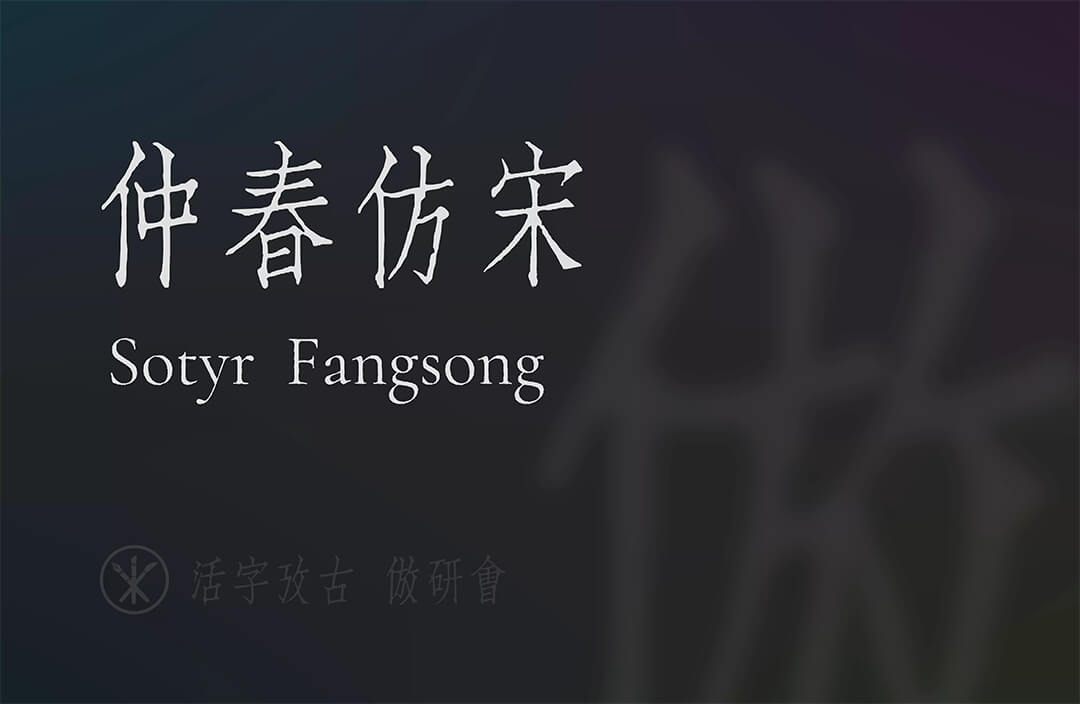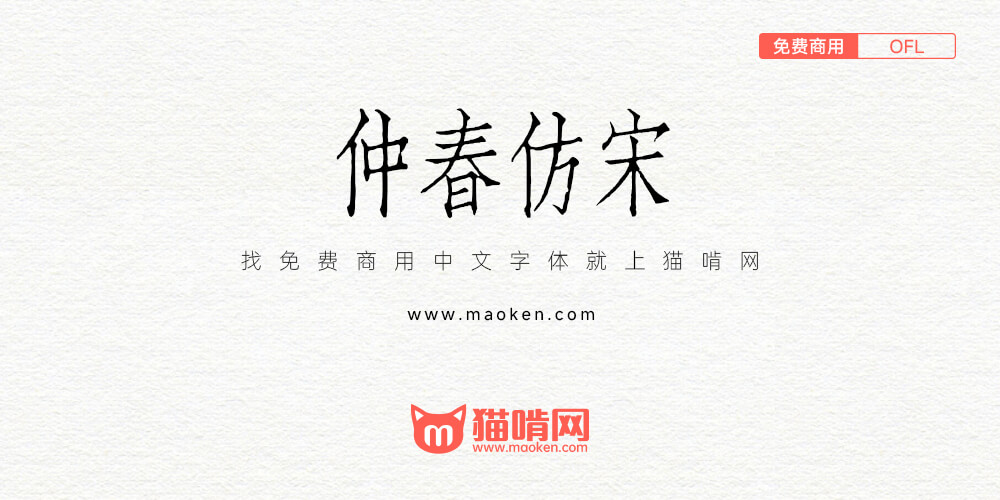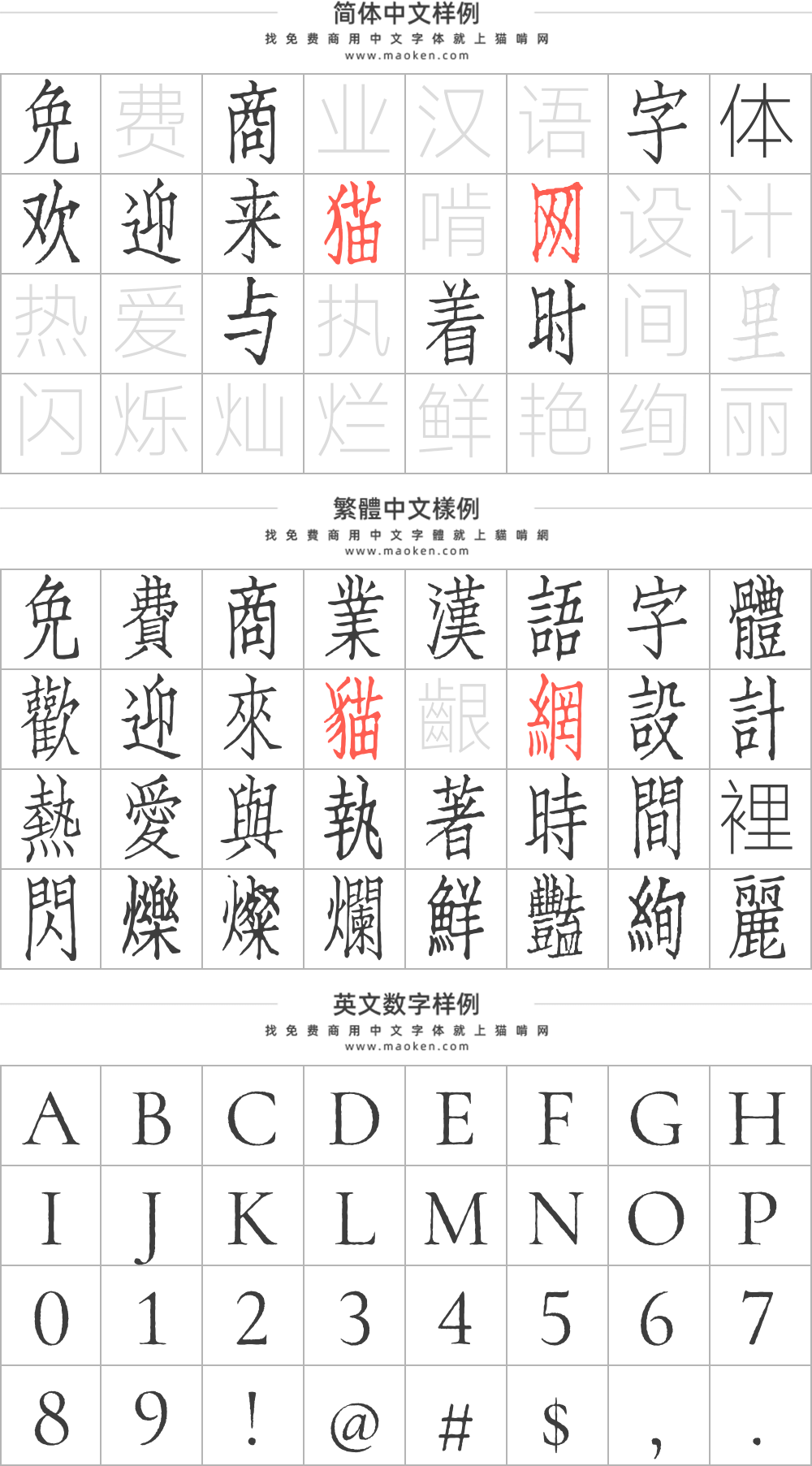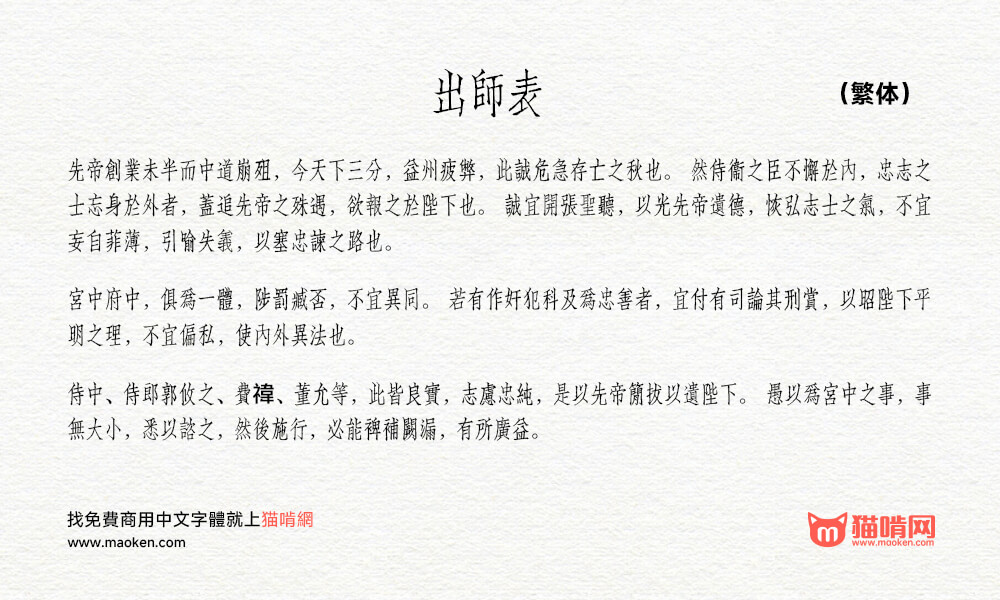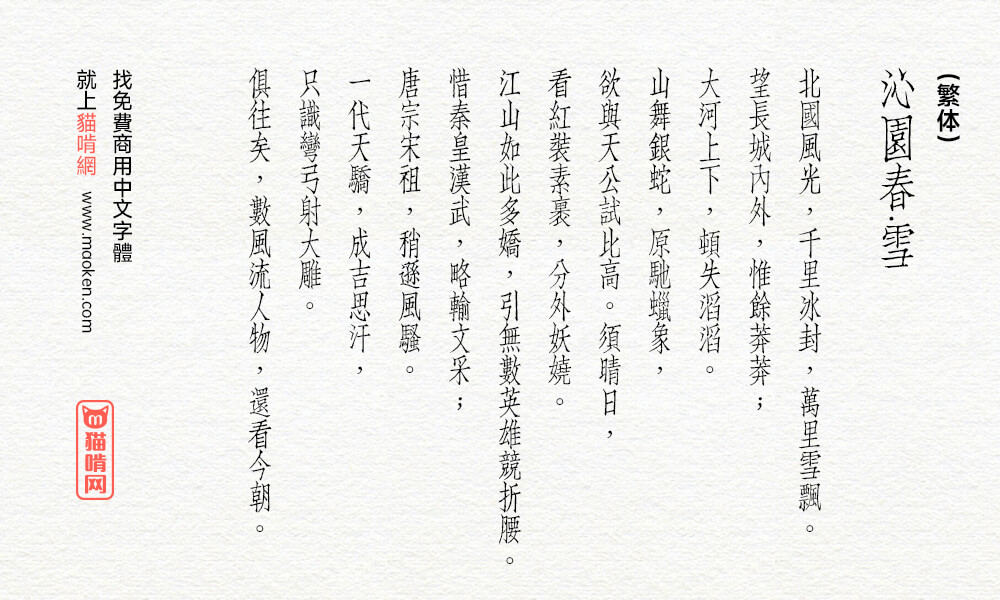
「仲春仿宋」项目是对上世纪聚珍仿宋二号长体铅活字字形进行的数字化。采用直接复刻办法,从印刷品扫描件中提取字形并封装为字体。
项目尚处于开发和测试阶段,其中的缺字、丑字不少,远不及正式版发布的程度。简化字部分是基本没有的,也不太推荐用于现代汉语文本的排版,还请各界朋友多多包涵。
开发故事
若论哪套长体仿宋最为著名?熟谙近现代印刷史的同志,恐怕大都会脱口而出「聚珍仿宋」。不过聚珍仿宋的长体铅字自身又包含多种字号,哪一种最具代表性?这个问题的答案或许在同志们的脑海中能浮现出,但落实到具体字号层面,就不那么好回答了。
聚珍仿宋二号长体铅字,造型妍美多姿,而又因其字号适中,常应用于正文排版而不是标题和夹注。相比于头号字的直健、三号四号字的间架异化处理、五号字的细密,二号字的字形可以说是最丰富地展现了聚珍仿宋家族的风味。同时,上世纪末,聚珍仿宋二号长体经过史云鹏的大力推广,成为了工程类制图常用的手写体。工科出身的朋友们,你们当年有没有练习过呢?
聚珍的头号方体长体、二号方体,市面已有产品,而尚无二号长体产品可用。
在印刷品样本方面,现在开放的电子化扫描件非常多了,缺少的只是对其中的字形进行提取封装的工作。这个工作量不小,所以从今年(2025)1 月开始,我们又合作开发了一种切片工具和一种封装前处理工具,效率大为提升,小组内的同志们拊掌称奇。
总之,「仲春仿宋」是传统汉字美学、印刷和数字化技术、新生产力结合的产物。
问:「为什么要叫『仲春』」呢?
答:这个项目是乙巳年仲春开始进行的。此外「仲」有「排行第二」的意思,而「春」的声符「屯」又有「聚集」的意思;二者结合,与「聚珍二号」暗应。「Sotyr」是「聚珍」的谐声域。
愿景
接下来的补字工作,除了采样更多的印刷品之外,缺字的补充暂时计划通过手写的方式来进行。今后空闲的时间恐怕不多,能有更新的机会那就要敲锣打鼓了。怎么办?我并不知道。
- 各印品初步切片、遴选、封装
- 《蓼园诗钞》《忍古楼诗》《味闲堂词钞》《纯飞馆词》《毛泽东选集》字形修整
- 《说文通检》所获字形修整
- 西文、标点完善
- 其他字形增修
- 字符集补完
- 常用字(传统汉字)
- 常用字(简化字)
西文、阿拉伯数字和半角标点,基于 Cormorant 修改而来,其许可证书同样是 SIL Open Font License 1.1。
10 月 13 日,v0.22-beta 偷偷发布,字符集大为扩充,简体基本补齐,也算小小地公测了一下。还未读过 v0.22-beta 更新记录的同志,还请先去了解一下更新内容。字体中的错误尚未传播太广,正是发布修正、餍足群友“御御众口”的好时机!!
v0.23-beta 修正了由「讠㐅」同志使用瞪眼法排查出的数十个错误字形、修正了 OpenType 特性中的一些错误,并增加了一些常见的扩展区字符。此版本发布后将保持一段时间不再发新版,以更全面地记录问题、减少发版次数、便利用家。
此次更新后的主要风险是:AI 生成的字形存在错形。经由网友 Blezig、渚 等人的測試,目前已经整体筛查过两遍,但仍不能保证绝对的正确。在使用中遇到的问题、发现的错误,烦请仍在 Issues 中提出,或者致信给我。
自仲春仿宋的首个公开测试版发布后,收到了各界朋友传来的反馈。古籍、文创和主题美化方面的同志十分喜爱,同时大家也提出了许多修改意见,非常感谢大家的关注!
此次发布的 v0.16-beta 是仲春仿宋的第二个公开测试版,经过一个多月痛苦的修字终于得以跟朋友们见面。
此次更新的主要内容为:
- 增加简入繁出版本,可以便利惯用简化字的用户。这份简入繁出的文件是通过 TCFontCreator 生成的,部分缺少的字使用了罕见的异体字进行替换,使用时需要注意。
SotyrFangsong-S2T-Regular即为简入繁出版。 - 新切了二十余本书籍,扩展了辖字数量。其中对《新曲苑》的采样,增加了大量白话文用字。
- 修饬了大量在上个版本中印糊、缺墨、歪斜等的丑字。
- 略微加粗西文、数字、西文标点。
- 统一了中日韩标点的字形风格。